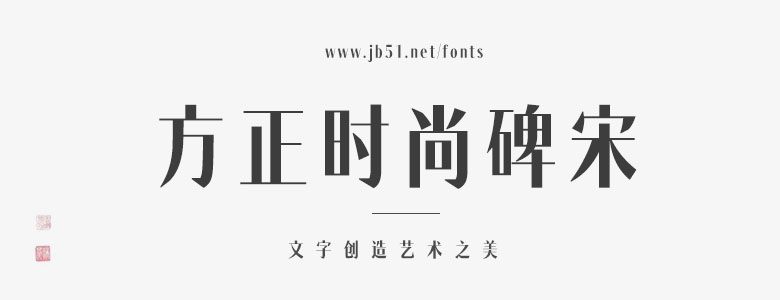
方正時(shí)尚碑宋家族是一款標(biāo)題展示類字體,可用于但不限于時(shí)尚、藝術(shù)、極簡(jiǎn)產(chǎn)品、性冷淡風(fēng)格等場(chǎng)景。尚碑宋獲得GDC Award 2019 專業(yè)組 / 視覺傳達(dá)類 / 文字設(shè)計(jì) / 銀獎(jiǎng)。筆形源自魏碑《龍門二十品》與現(xiàn)代宋體審美的結(jié)合,特別在撇捺曲線末端和勾點(diǎn)的微微斜切造形上,既抽象了銘刻的痕跡,又在功能上避免了飄尖,讓筆形既鈍又峭,且某些交叉處自然收縮而優(yōu)化了顯示,在幾何構(gòu)成與書法結(jié)體、功能與形式上自然融合,順應(yīng)當(dāng)今屏幕顯示與印刷工藝的高清晰還原,呈現(xiàn)一種極冷靜、極銳利、極簡(jiǎn)潔的文字雕刻之美。